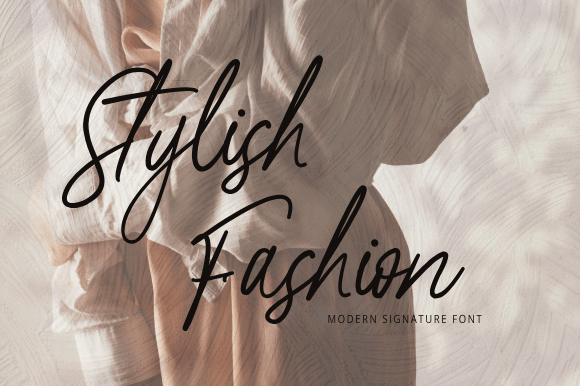
Stylish Fashion
Trouver les bons éléments de conception peut être un défi, mais Stylish Fashion propose une collection exceptionnelle qui rehausse instantanément votre travail.
Que vous créiez des produits POD (impression à la demande), des invitations de mariage ou des visuels pour les réseaux sociaux, Stylish Fashion est un choix idéal.